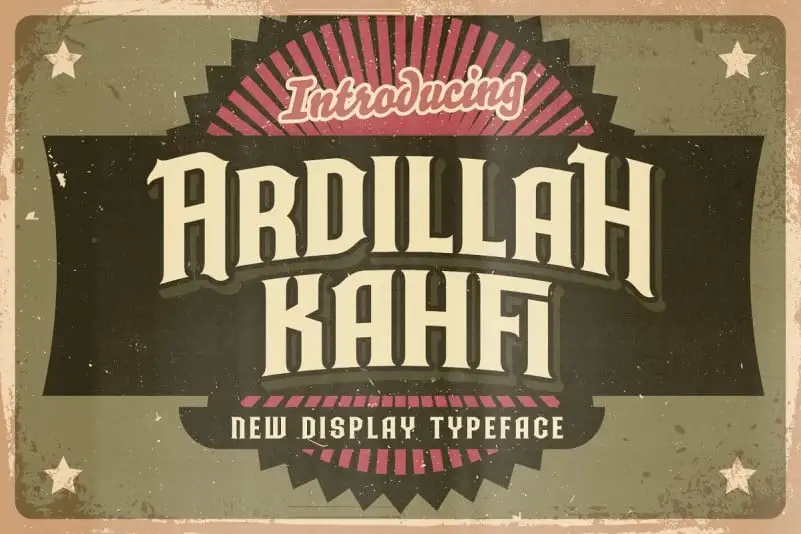
Ardilah Kafi Display Font – Download Grátis
Ardilah Kafi Display Font é uma tipografia de exibição inspirada por cultura clássica ocidental, revestida com um toque vintage que fazendo eco ao passado. Este design foi criado pelo designer de fontes Stringlabs. Ardilah Kafi traz uma sensação amigável e nostálgica, oferecendo um visual vintage impactante. Essa tipografia é uma verdadeira obra-prima de beleza e atratividade. Ardilah Kafi se destaca em designs modernos e clássicos, destacando-se por seu formato romântico e forte, além do cuidado com os detalhes. Este design é perfeito para aqueles que buscam uma fonte única e intrigante para seus projetos digitais.